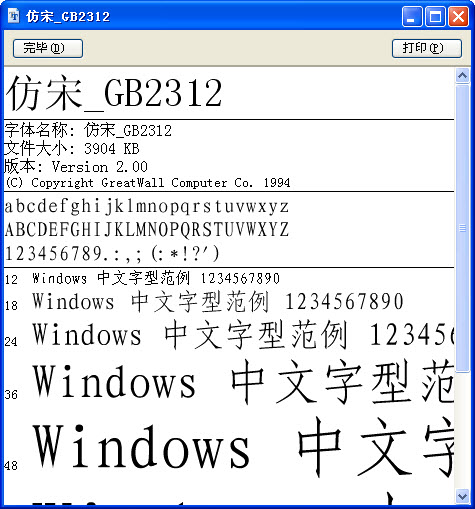
仿宋gb2312.shx是一種中文宋體書法的cad字體,宋體婉約輕柔,精簡大法官,讓你的平面設(shè)計、海報制作有著獨特的美感和觀賞性,來綠色資源網(wǎng)免費下載體驗吧!
什么是仿宋_gb2312字體官方版?
公文標準字體之一。仿宋是字體名稱,GB2312是字符編碼名稱,屬簡體中文編碼的一種,簡體中文自1980年代以來通常使用中華人民共和國國家標準總局公布的GB 2312,以及其后繼的GBK和GB 18030中文編碼。近年來隨著Unicode跨語言編碼集的出現(xiàn),也被廣泛使用。所以通常說的仿宋就基本上是仿宋_GB2312了。